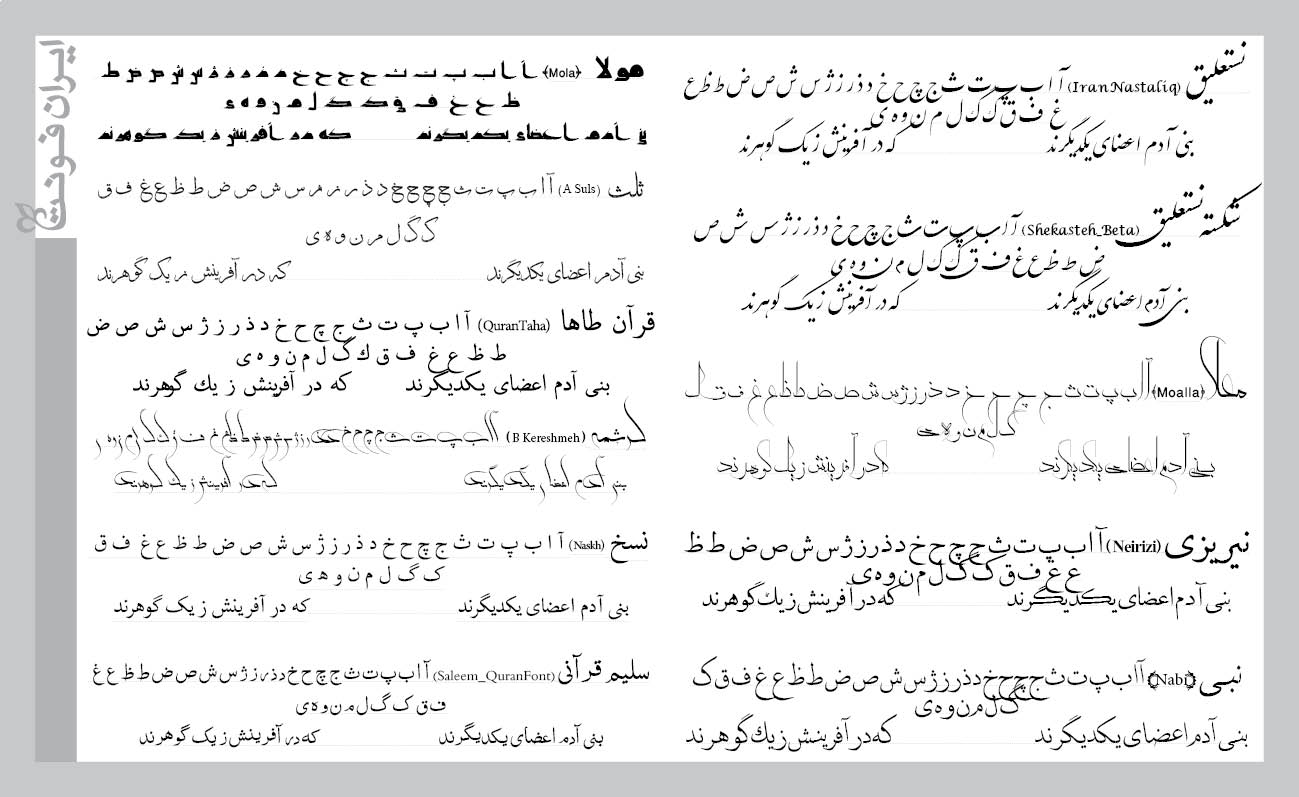
بالاخره اصلی ترین محصول ایران فونت (که وعده اش را داده بودیم) عرضه شد. و این یعنی حدود 750 فونت فارسی بدون تکرار. و این یعنی تحولی در عرصه نگارش فارسی. این بسته منحصر به فرد که برخی از ویژگیهایش در ادامه ذکر خواهند شد در دهه سوم شهریور ماه منتشر شد. تا همگی به این باور برسیم که خط فارسی بسیار زیباتر از آن است که در چند ده فونت سالهای پیش خلاصه شود.
حقیقتا کار بزرگی صورت گرفته است. صرف 3 سال زمان و انرژی و بررسی هزاران فونت این رسم الخط از سراسر جهان، جمع آوری، بازبینی، گلچین و اصلاح و ارتقای آنها اتفاق کمی نیست که بتوان به سادگی از آن گذشت. خروجی این کار بسته ایران فونت (بانک قلمهای ایرانی) شده است. که به اعتقاد ما با توجه به قابلیتهای منحصر به فرد این بسته، حرفهای بودن، جدید، جامع و یکپارچه بودن؛ بهترین بستهی فونتی خواهد بود که تا حال حاضر به بازار عرضه خواهد شد. این تنها یک بخش از محتویات بستهی جامع فونت فارسی است.
محتویات این بسته شامل موارد زیر است:
1. بسته جامع فونت فارسی
حدود 650 فونت فارسی ویرایش و بازسازی شده + حدود 25 فونت جدید انحصاری (از قبیل فونت پرشین گلف). پیشوند تمامی این فونتها B میباشد تا از بهم ریختگی در نوار فونتهای شما خودداری گردد و بصورت یکپارچه در کنار هم قرار گیرند. با داشتن این بسته مطمئن خواهید بود که بدون استثنا تمامی فونتهایی که در سراسر محصولات فارسی و فارسینویسها وجود دارند را خواهید داشت. توضیحات بیشتر
2. بسته حرفهای فونت فارسی
این بسته 45 گانه با پیشوند ir شامل فونت های حرفه ای است که از قابلیتهای بسیار ویژه برخوردار هستند. برخی از این ویژگی ها را در زیر ذکر می کنیم:
الف: پشتیبانی از تمام حروف فارسی، اردو، عربی، انگلیسی
ب: پشتیبانی از کارکترهای خاص بطور ویژه همچون علیه السلام و…
ج: پشتیبانی از تکنولوژی های جدید فونت فارسی و همچنین کرنینگ (فرورفتگی حروف)
3. بسته فونت های خطی
بسته ای شامل 20 فونت خطی منحصر به فرد و پرکاربرد (تصویر). که از مهمترین آن میتوان به فونت شکسته نستعلیق، نسخ، ثلث، معلی و… اشاره کرد.
4. بسته فونت های کارکتری (سیمبل)
5. کتابچه راهنمای فونت فارسی
این کتابچه ضمن ارائه پیش نمایشی از همه فونت ها اطلاعات بی نظیری در رابطه با روش استفاده از فونت ها و چگونگی انتخاب یک فونت برای موارد مصرفی متفاوت و… را در اختیار شما قرار میدهد.